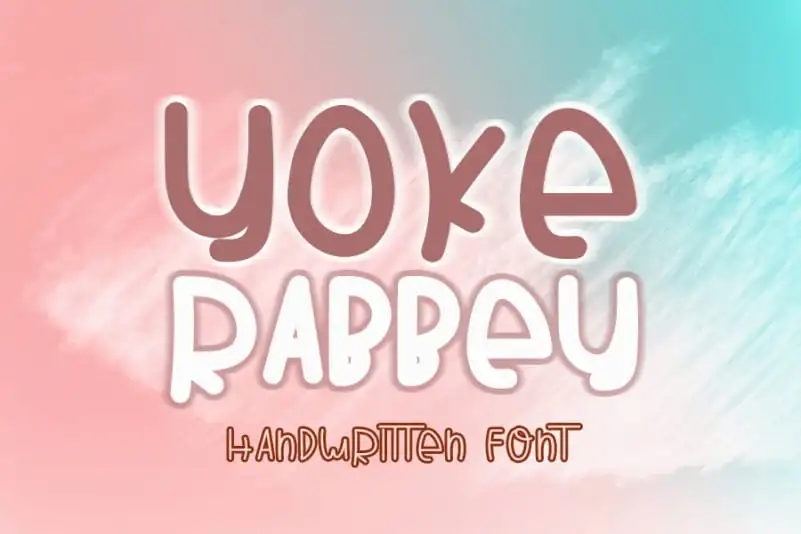
YOKE RABBEY Script Font
A fonte Yoke Rabbeey Script é uma escolha inteligente para projetos onde você precisa manter a sofisticação das letras antigas enquanto mantém um toque moderno e fresco. Esta font tem uma rica influência de escrita decorativa, mas também traz uma leve atualidade que faz dela perfeitamente adequada para diversos tipos de ideias criativas – desde cartões de visita até títulos de apresentação ou mesmo materiais de embalagem estilizados. Seu uso versátil e elegante a torna ideal tanto para designers gráficos como para quem usa seu trabalho diariamente. A Yoke Rabbeey Script é perfeita para aqueles que desejam incorporar um toque único, mas atemporal em seus projetos. Ela traz uma sofisticação que pode ser usada com confiança tanto nos materiais de escritório quanto no design de arte, sem perder sua versatilidade e capacidade de se adaptar às diferentes necessidades do seu projeto.